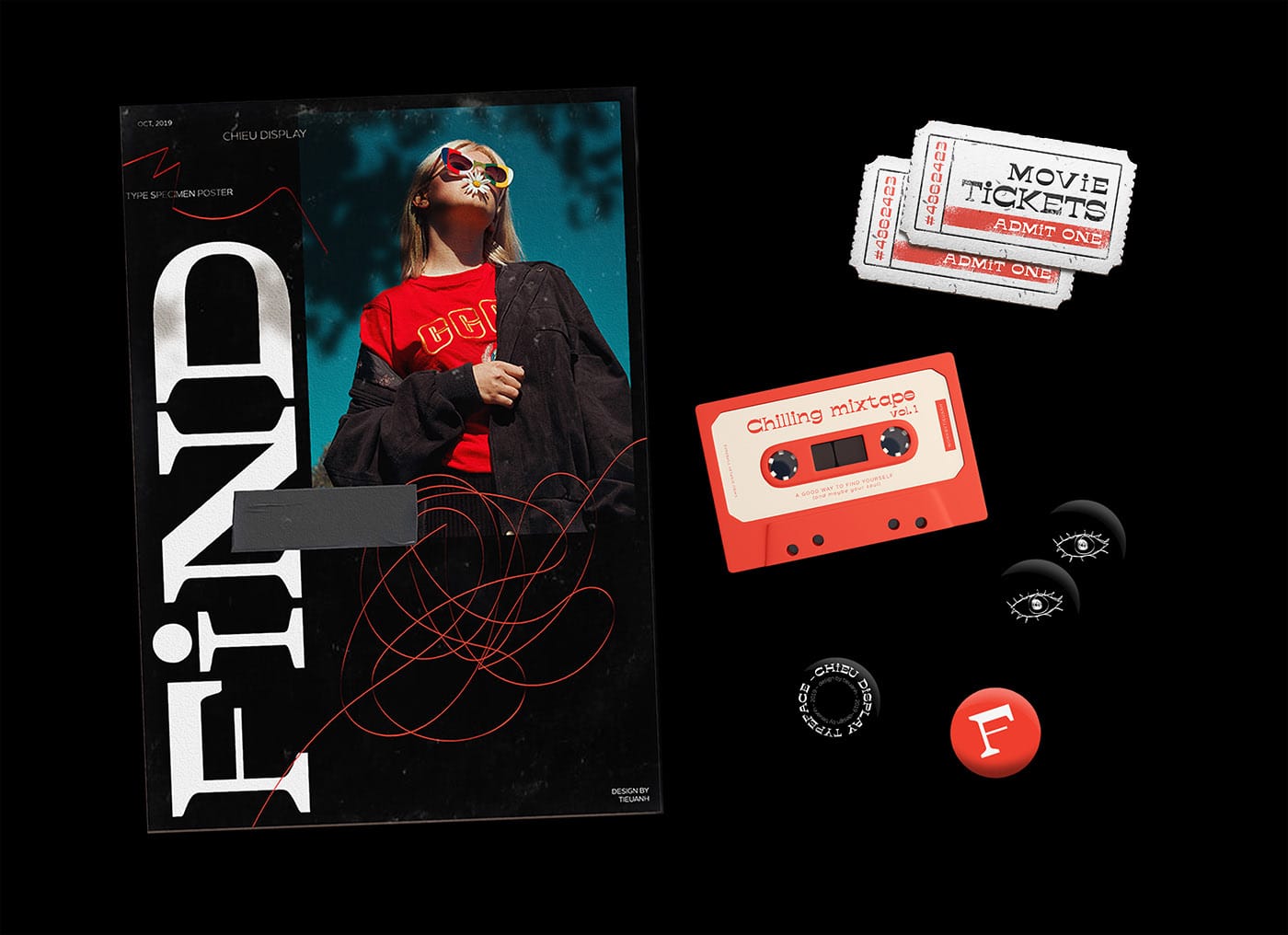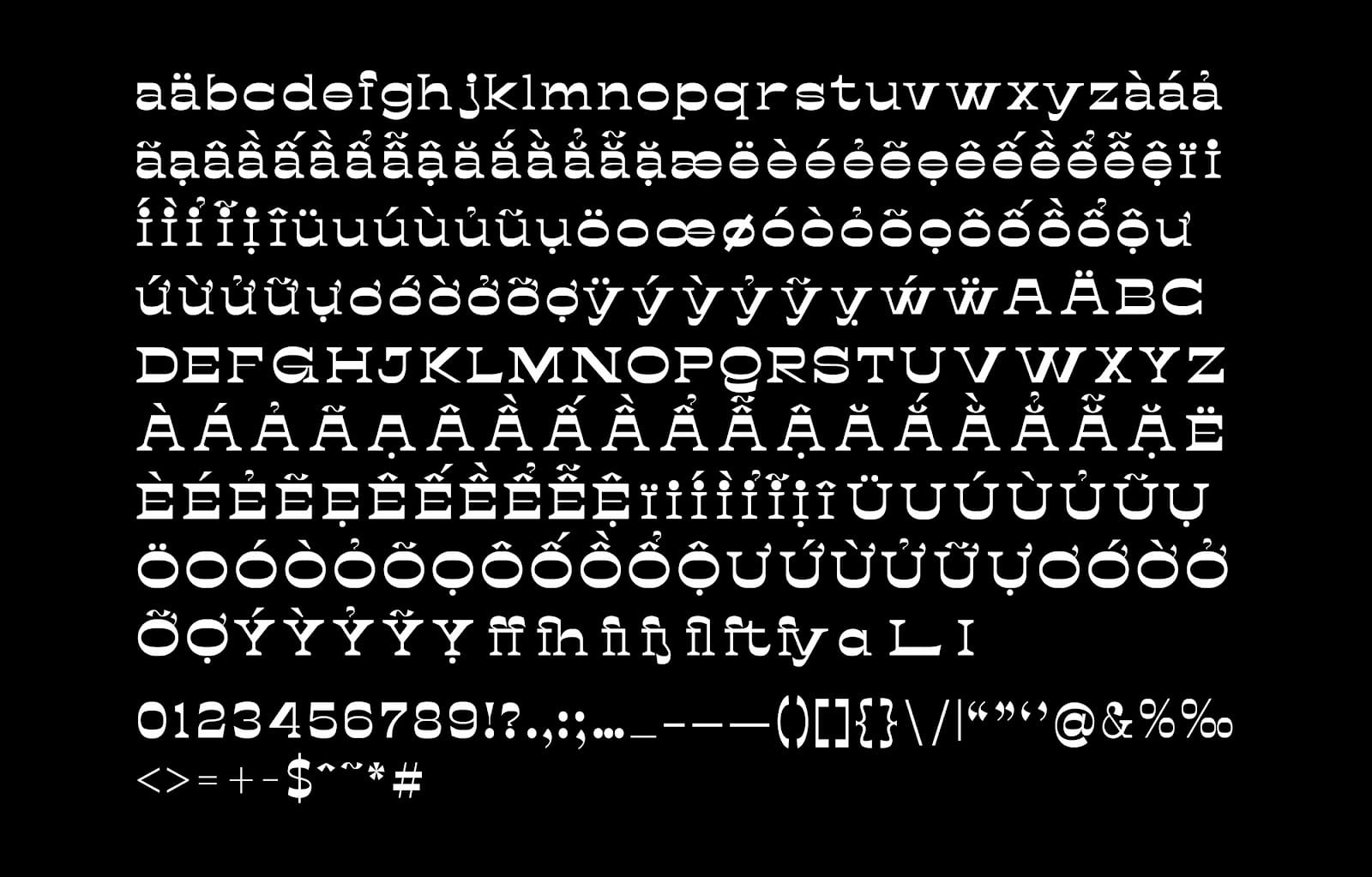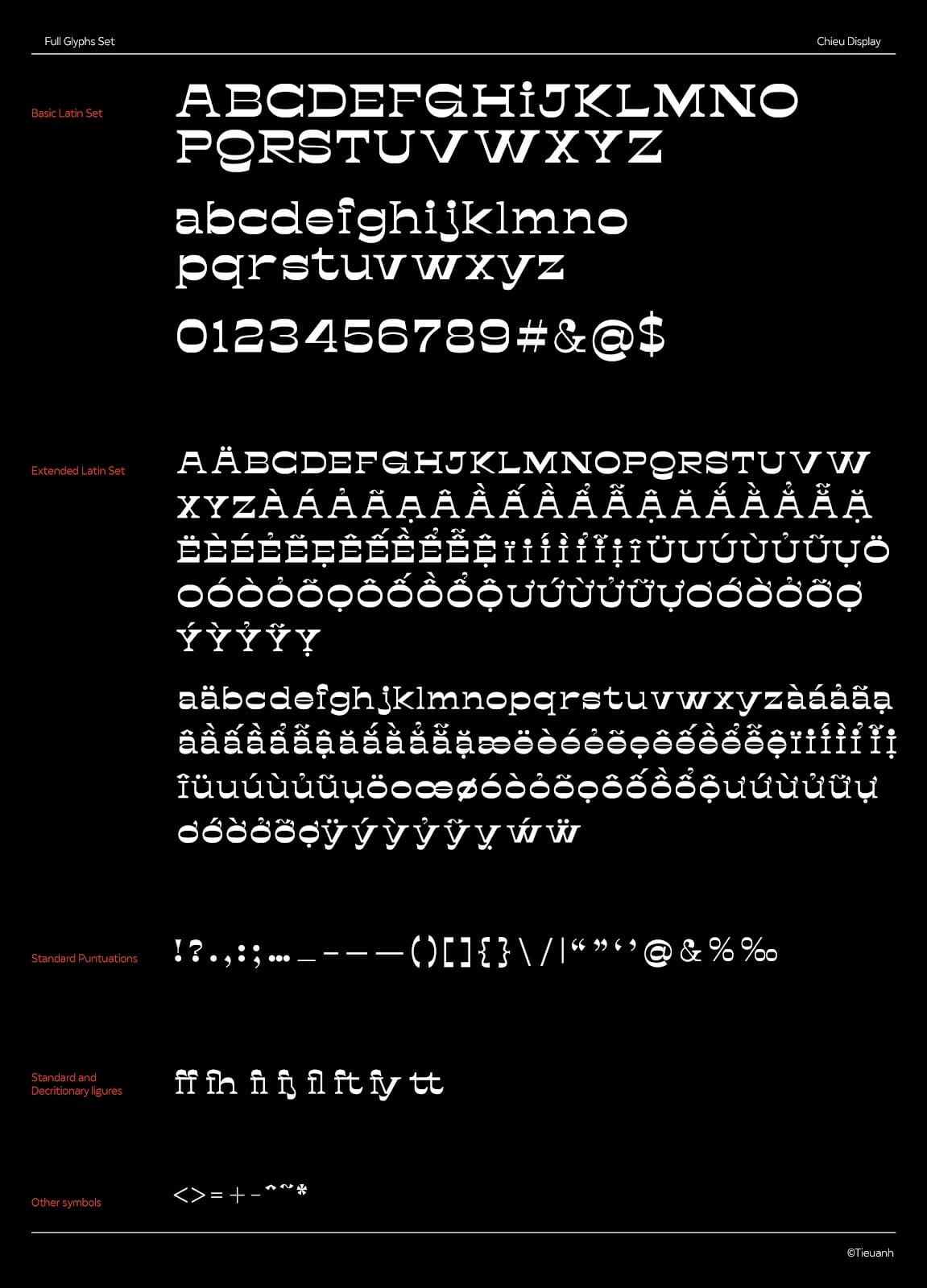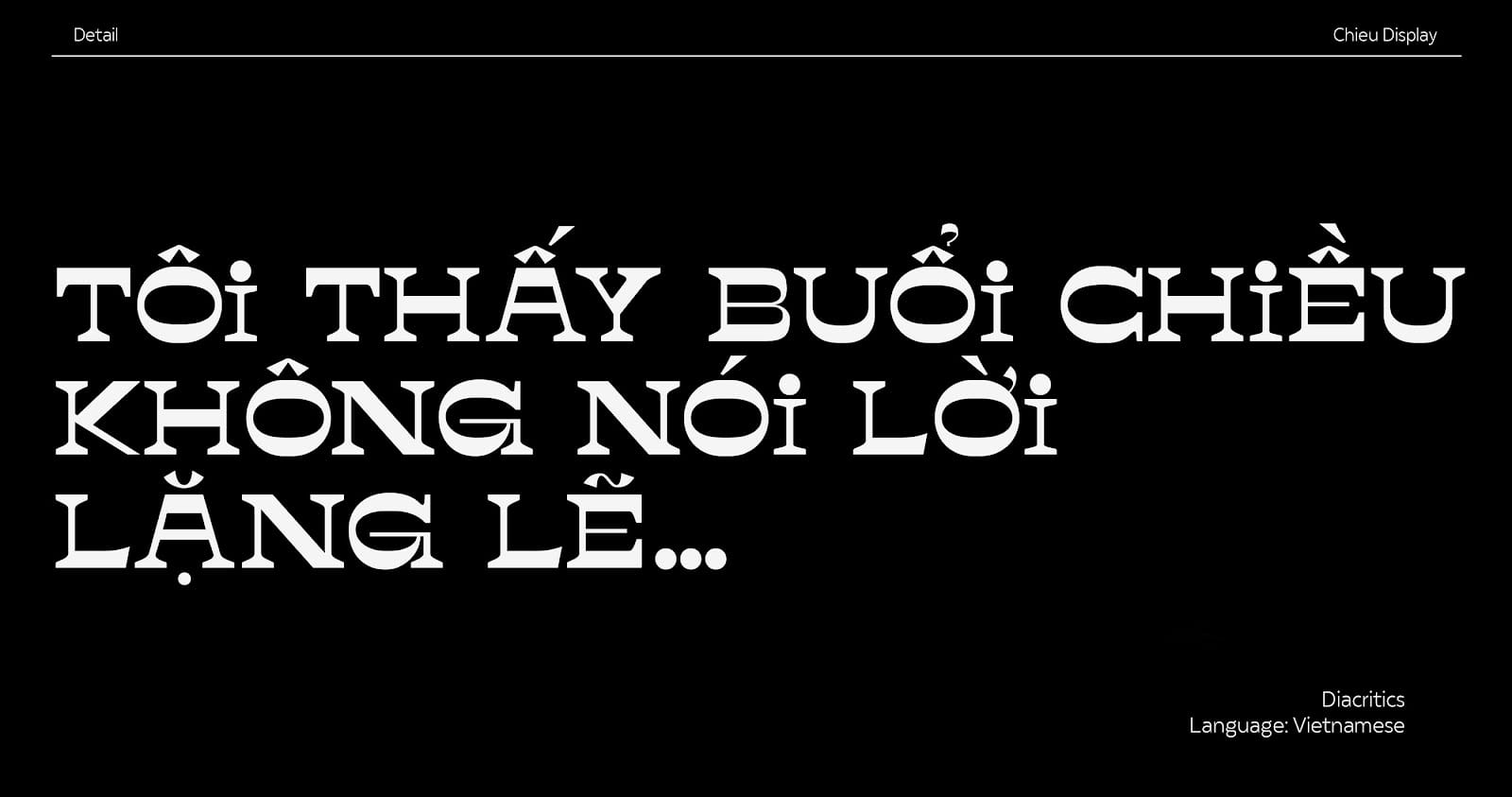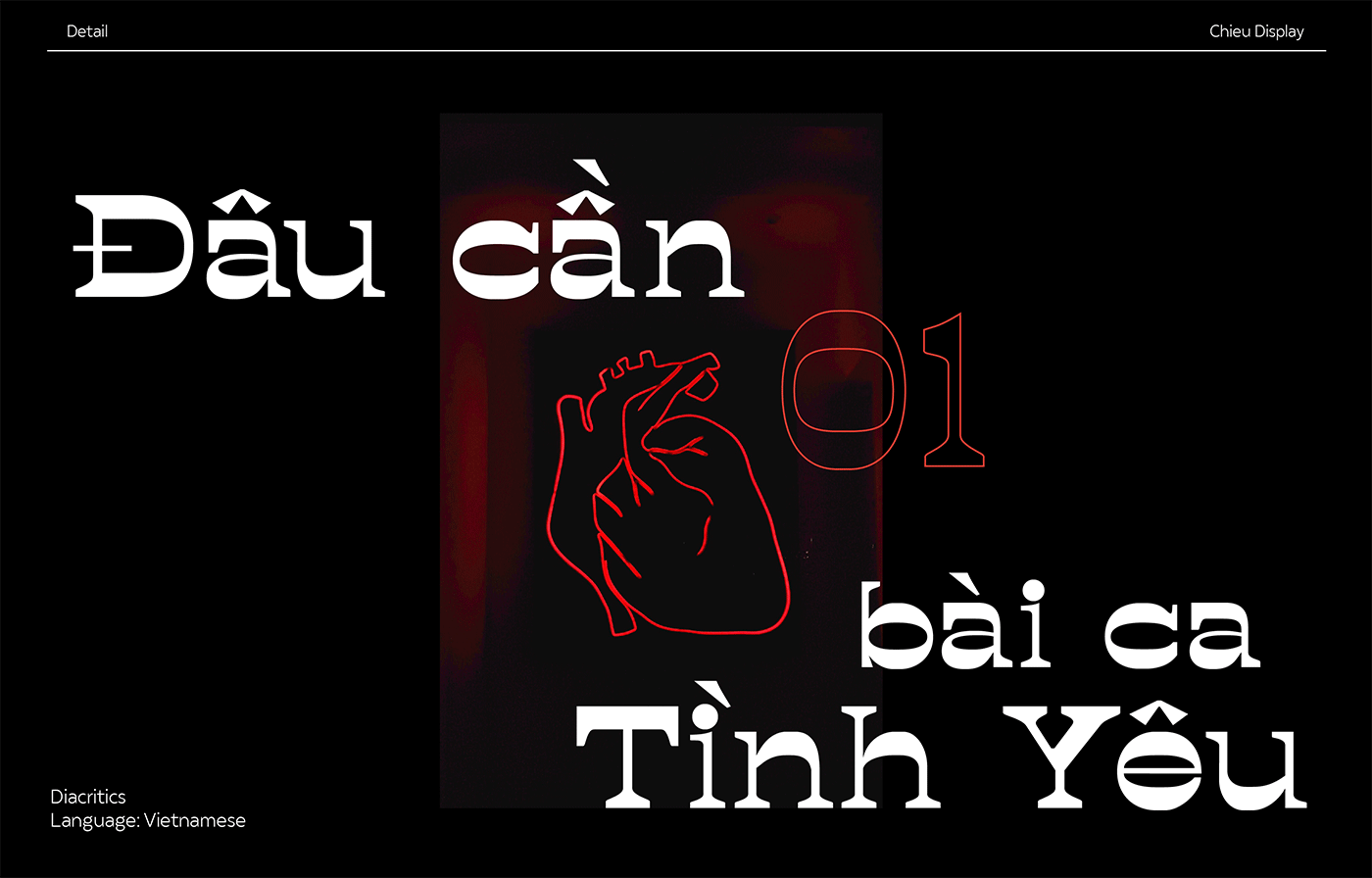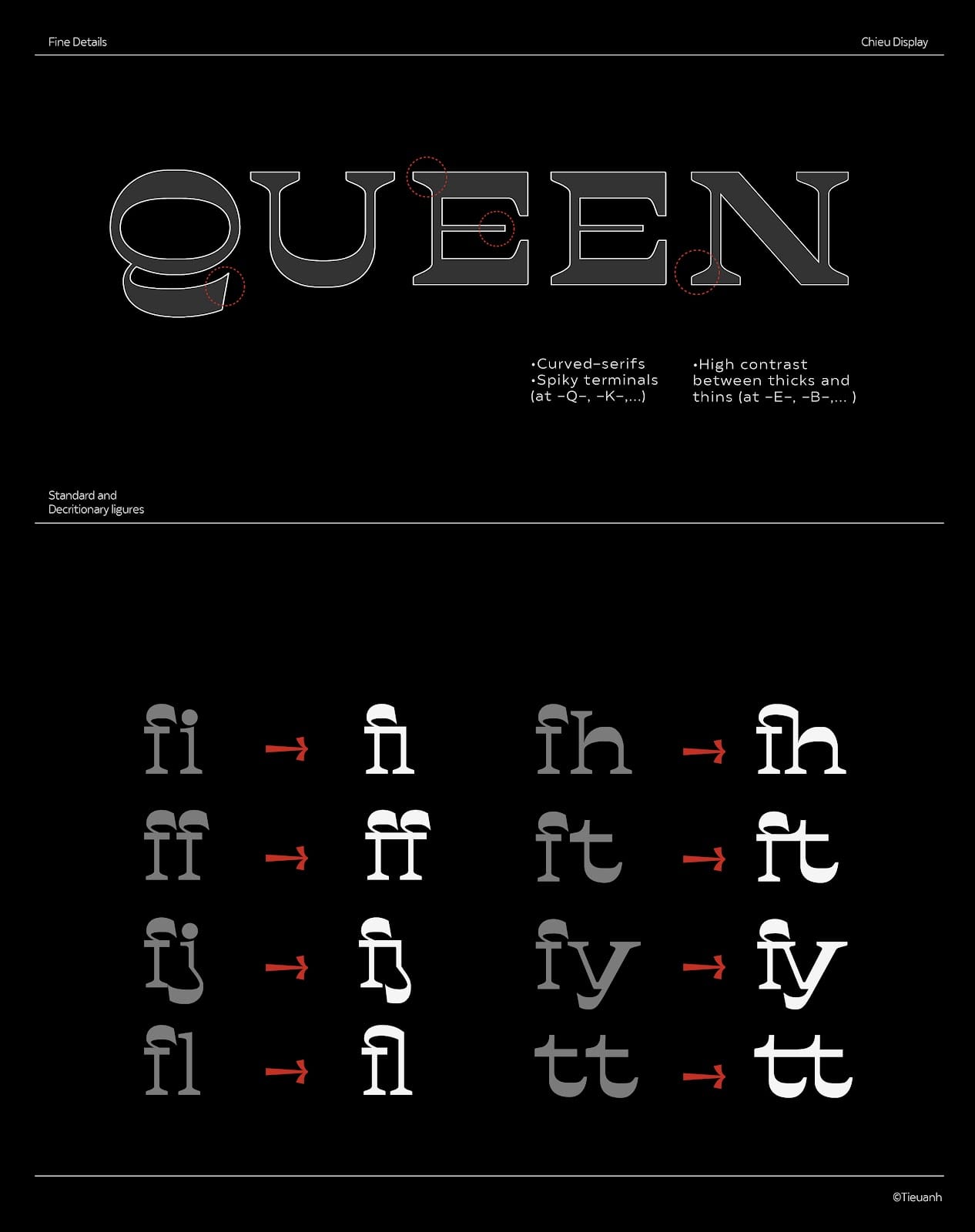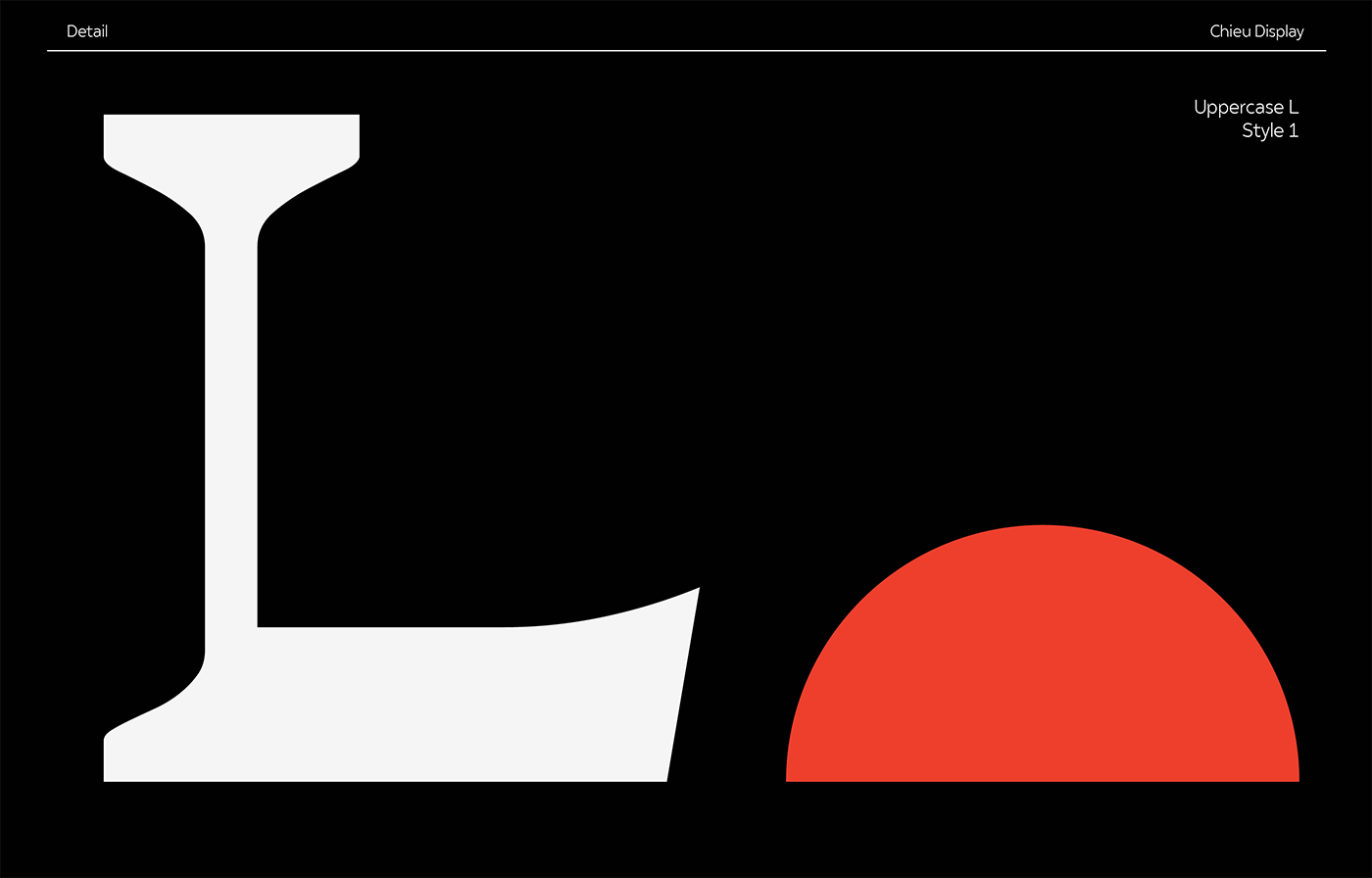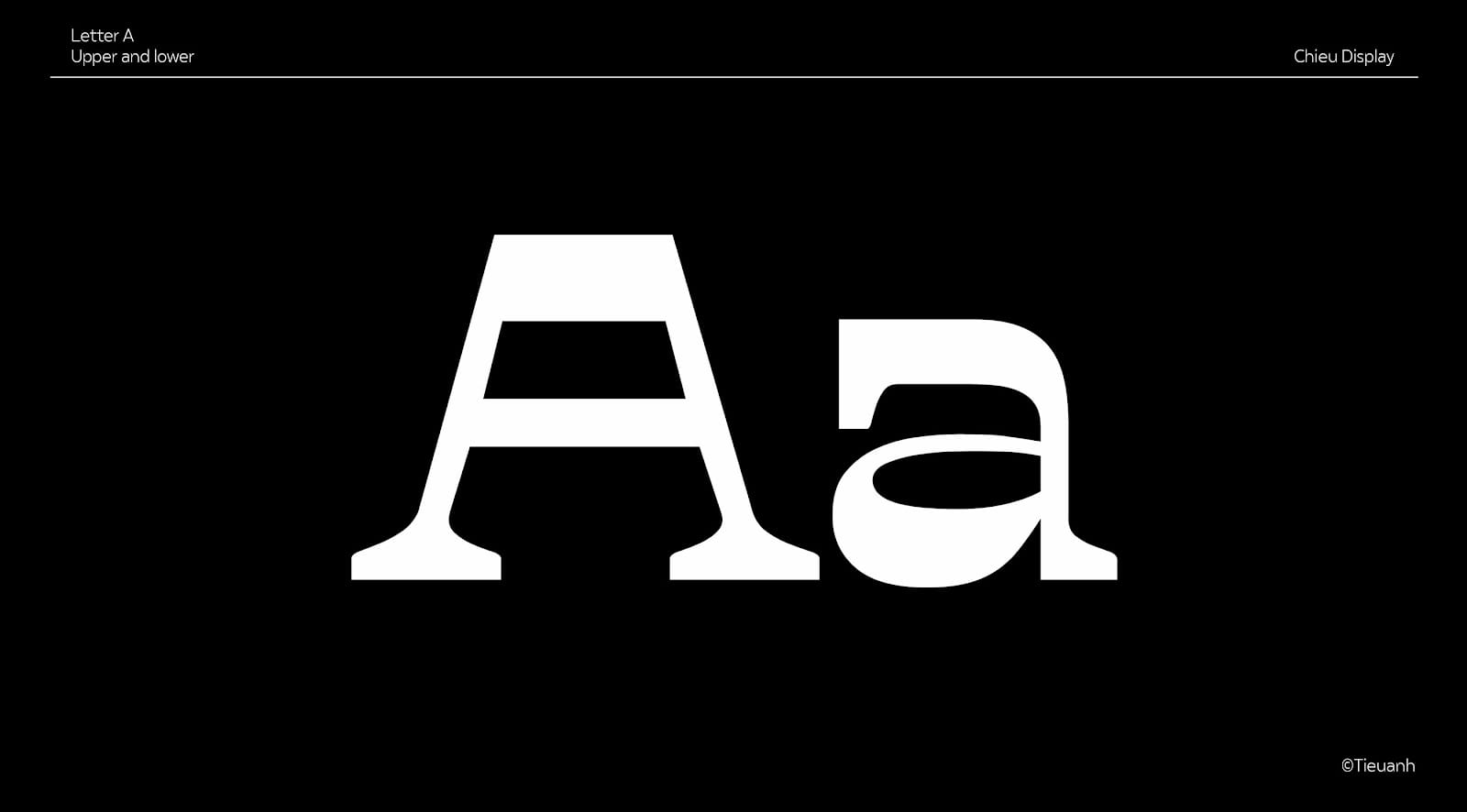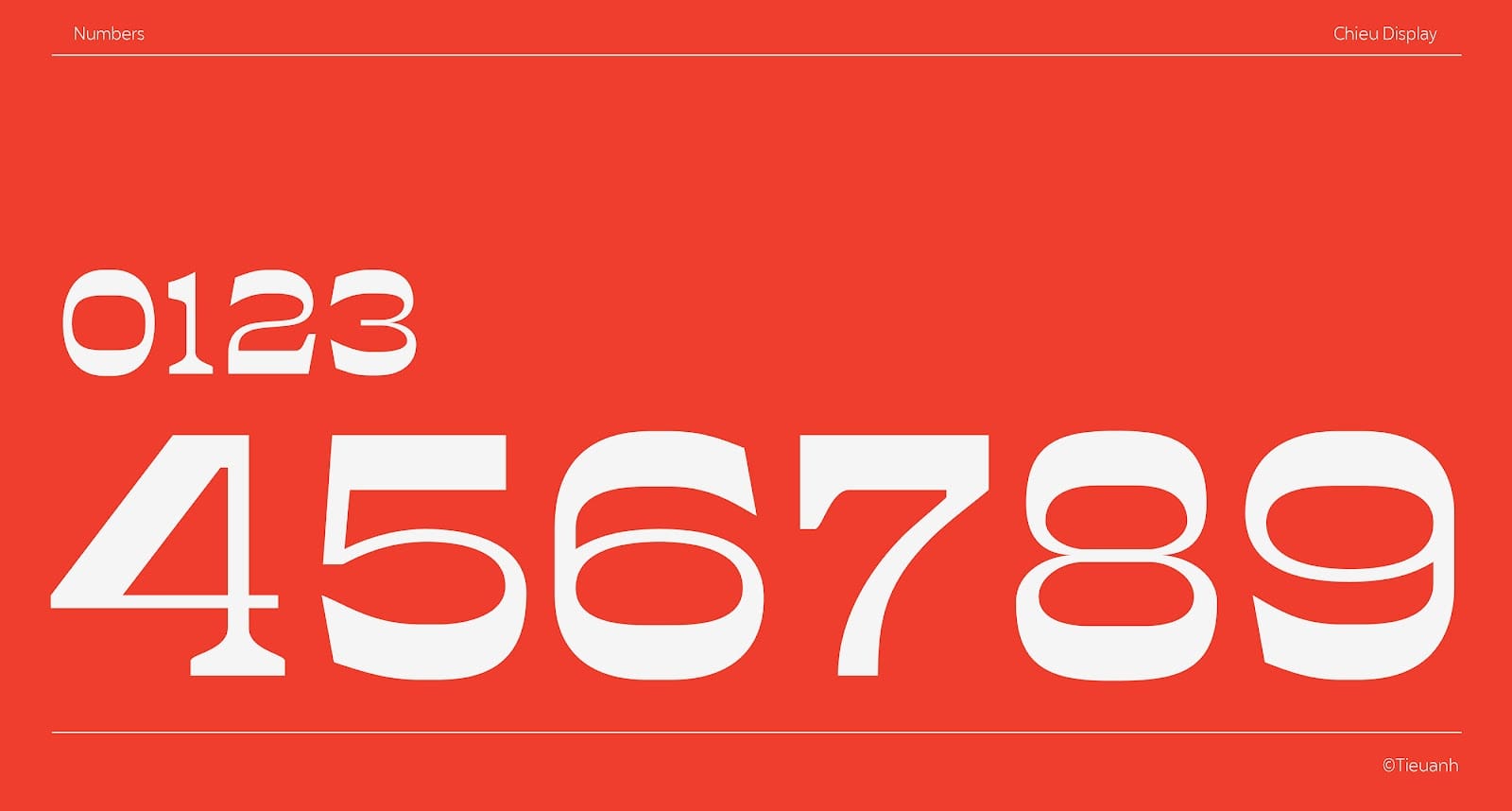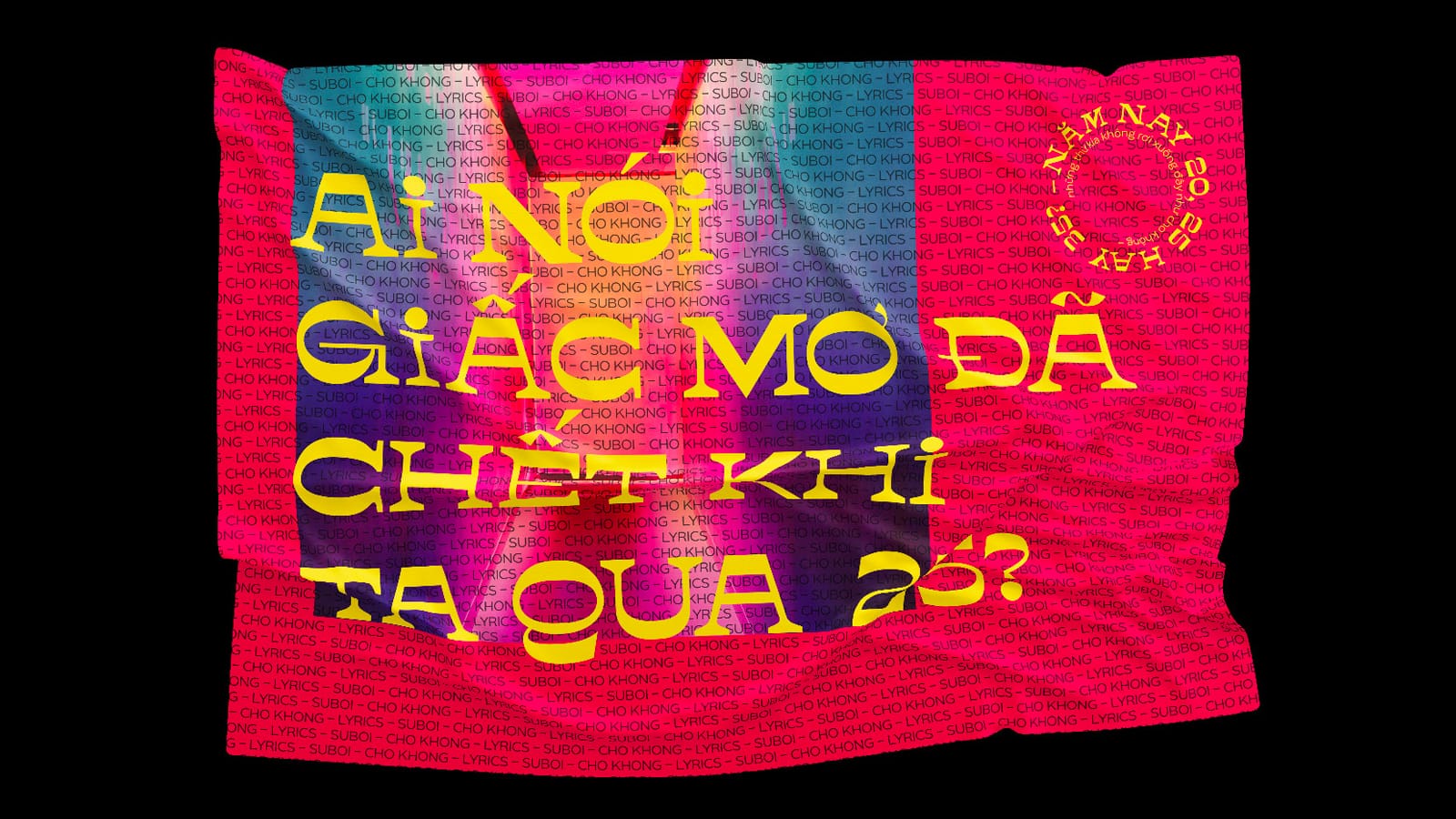
Chieu Display Typeface một font chữ Việt được thiết kế bởi Tieu Anh là một kiểu chữ tùy chỉnh serif với độ tương phản ngược. Điều làm cho CHIEU DISPLAY trở nên độc đáo là các đường cong kết hợp với form rộng.
Một số chữ cái được đặc trưng bởi sự tương phản mạnh mẽ giữa mảnh và mỏng hoặc có chân. Nó hoạt động tuyệt vời trên các áp phích lớn, tiêu đề, tiêu đề phụ, banner, tạp chí, poster phim, poster nhạc… và bất kỳ thiết kế nào mang phong cách hiện đại.